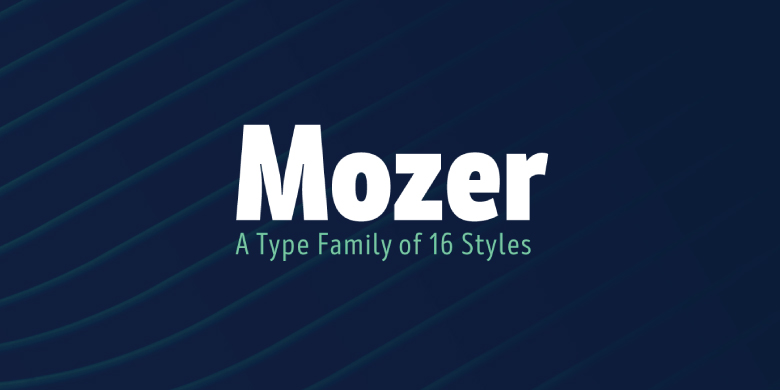
Mozer英文字体
Mozer是一个半浓缩的新怪诞风格家族,有16种风格,从细到粗,搭配真正的斜体。这种无衬线字体具有宽大的x高度、经济的宽度、适度的对比度和全方位的立体外观,非常适合作为头条新闻。无与伦比的易读性与独特的现代精神相结合,即使在离散的墨水陷阱等小细节中也能看到。
Fontfabric字体设计师知道,Mozer涵盖了扩展拉丁语、西里尔语和希腊语,并适用于大量OpenType功能,如本地化、连字;四种类型的数字,包括数字和表格;区分大小写的表格;替代品等等。
Mozer is a semi-condensed neo-grotesque type family of 16 styles, ranging from Thin to Black and matched with true italics. With a generous x-height, economical width, moderate contrast, and an all-around solid appearance, this sans serif typeface lends itself well to headlines. Uncompromising legibility meets a distinct contemporary spirit, visible even in small details like the discrete ink traps.
Fontfabric font designers know that Mozer covers Extended Latin, Cyrillic, and Greek and is suited with plenty of OpenType features, such as localizations, ligatures; four types of numerals including figures and tabular; case-sensitive forms; alternatives, and more.
OpenType Features
Stylistic Alternates
Common Ligatures
Discretionary Ligatures
Contextual alternates
Localised Forms
Tabular Figures
Proportional Figures
Diagonal Fractions
Denominator
Numerator
Subscript
Superscripts
Case Sensitive Forms
Ordinals